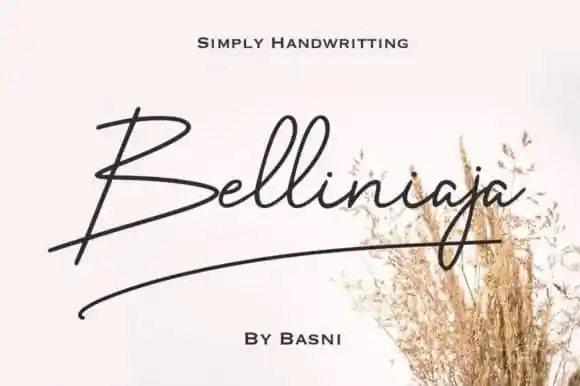
Belliniaja Handwritten Font
A Belliniaja Handwritten Font é uma deliciosa mistura de elegância casual que pode ser utilizada em diversas necessidades de design. Esta tipografia delicada e elegante foi criada pela bee.genin, conhecida por produzir tipos textuais cuidadosamente manufacturados. Seus caracteres distintos e redondos fazem dela um verdadeiro trabalho de arte. Inove seus projetos com a Belliniaja Handwritten Font – sua versatilidade impressionante certamente vai te surpreender. Ela é perfeita para criar designs excepcionais, seja em cartazes grandiosos, logotipos chamativos ou até mesmo mensagens personalizadas que irão cativar seus leitores. Adquira já a Belliniaja Handwritten Font e faça seu design soar autêntico e sofisticado.